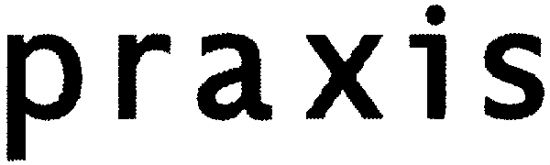
Das i kenn ich doch... bloß woher?
ich dachte erst an Trebuchet, aber die kommt auch nicht ganz hin...
mhh, ich kenn mich nich so gut mit fonts uas( zumindest nicht mit namen) aber so wies aussieht würde ich nciht auf einen font tippen sondern auf nen aftereffekt
woher hast du das bild?
Bitte nicht auf die kaputte Outline achten, das stammt wohl von einem Fax oder so, gesucht ist wirlkich nur der Font.